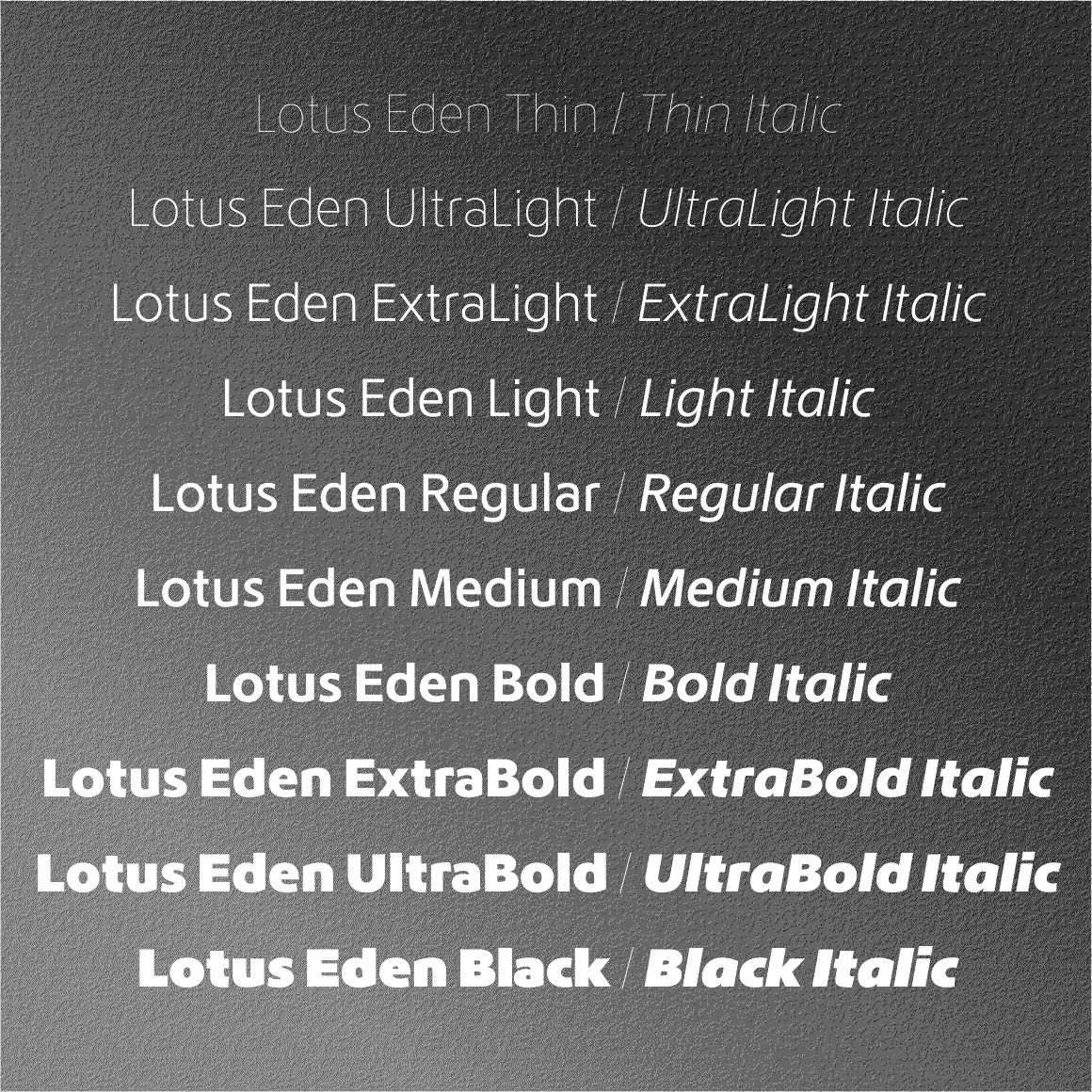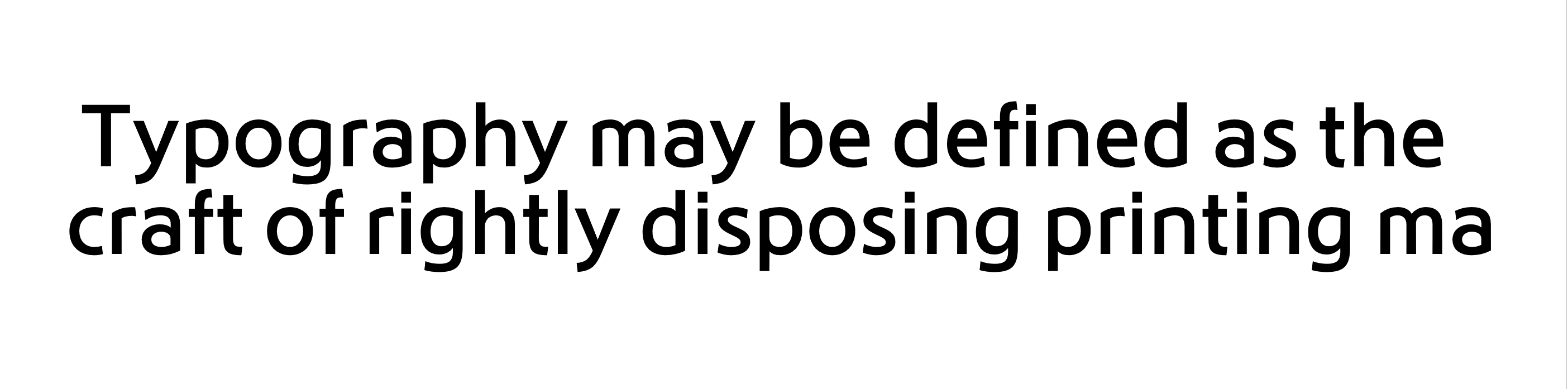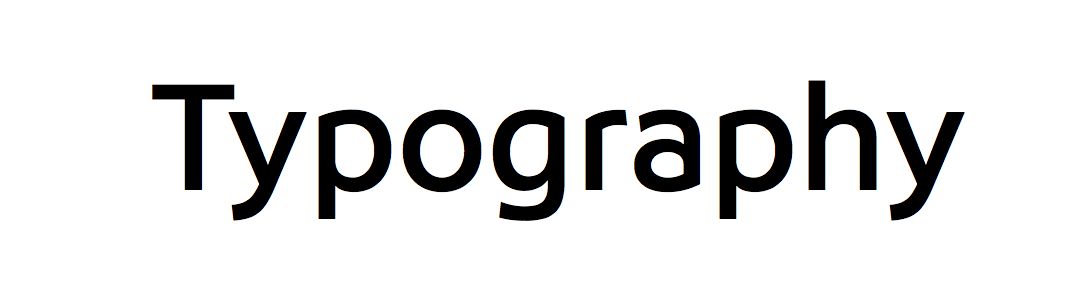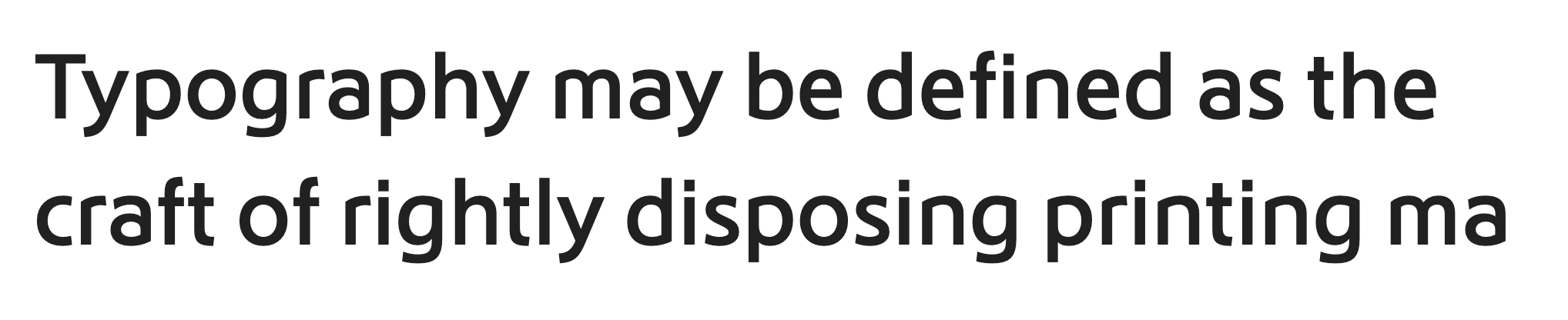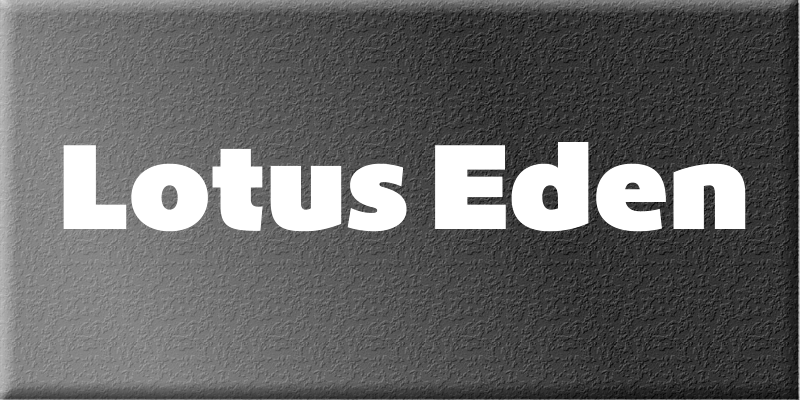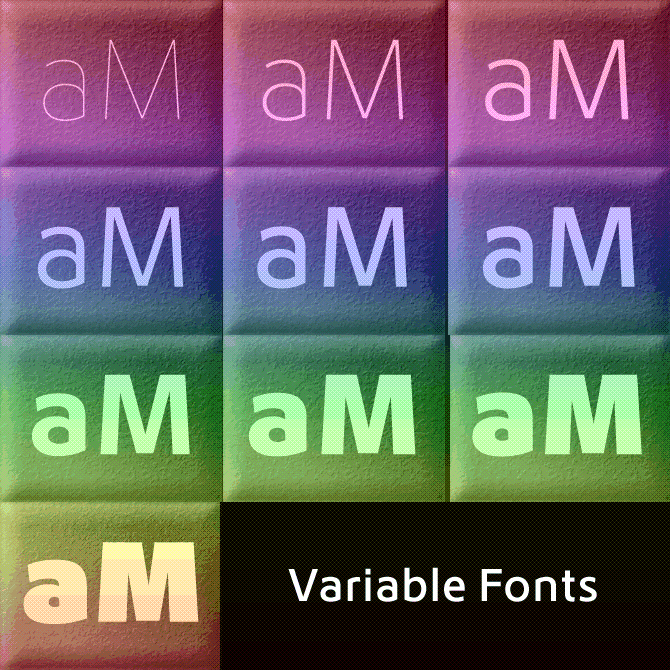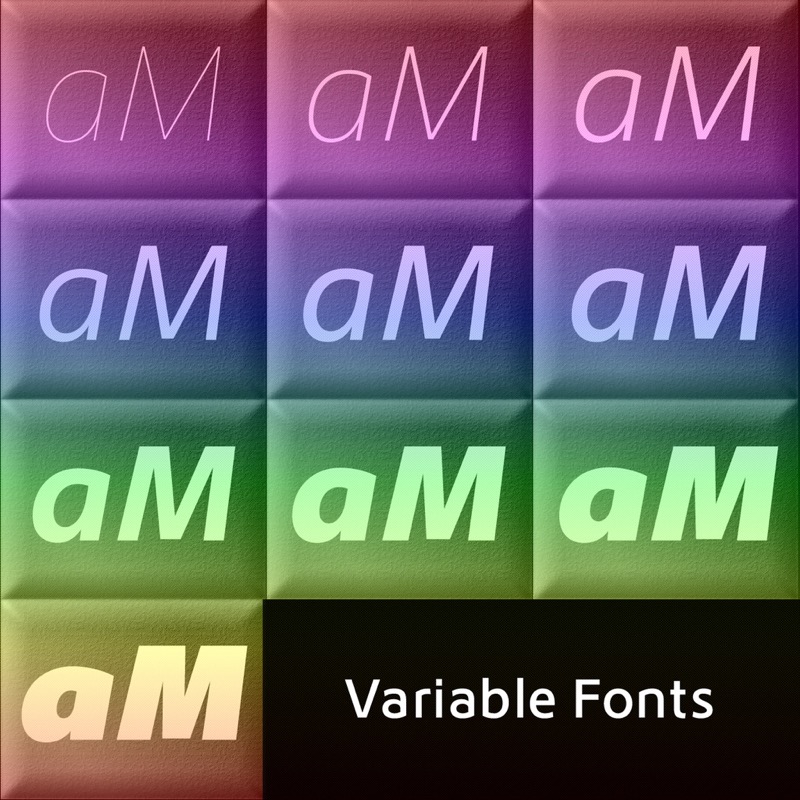
10ウェイト20スタイルの本格的な欧文フォント「Lotus Eden」
エスペラント語への対応を行い、グリフ数は657になりました。
また、ダイアクリティックの微妙な位置ズレの調整を行いました。
ウェイトを無段階に調整できるVariableフォント。
こちらはイタリック。
10ウェイト20スタイル、すべて使えます。
1987年に、第2回モリサワ賞 国際タイプフェイスコンテストの欧文部門で2位となった「Lotus medium」 を、10ウェイトの「Lotus Eden」として完成させました(フォントデザイン:佐賀野 宇宙)。
元になったのは、この書体です。↓
とってもモダンな雰囲気! 1987年に発表されたとのことで驚愕です。
Lotus Eden になって「Ty」のペアカーニングが設定され、そのまま組んでもぴったり収まりますね。今後使うのが楽しみな書体です。
「Ty」のペアカーニングが設定されてますから、普通にタイプすれば、このようにピッタリ収まります。
(手羽先さんが載せてくれた画像は、古いやつかな?)
大変失礼いたしました。こちらの環境の問題でペアカーニングが効いていませんでした。設定を変えて正しく表示できましたので再投稿します。「Ty」でペアカーニングが有効になり、美しく詰められることを確認しました。